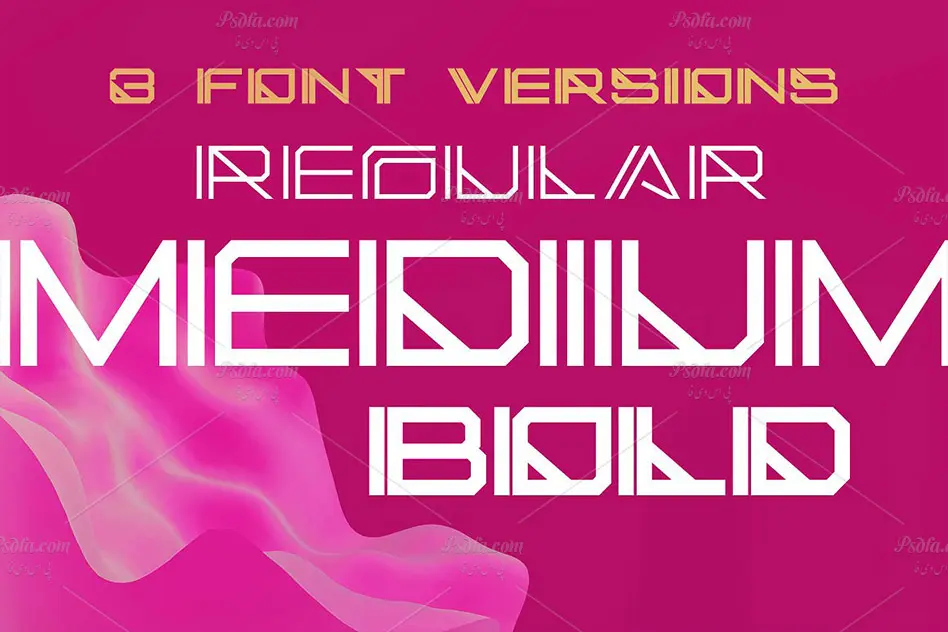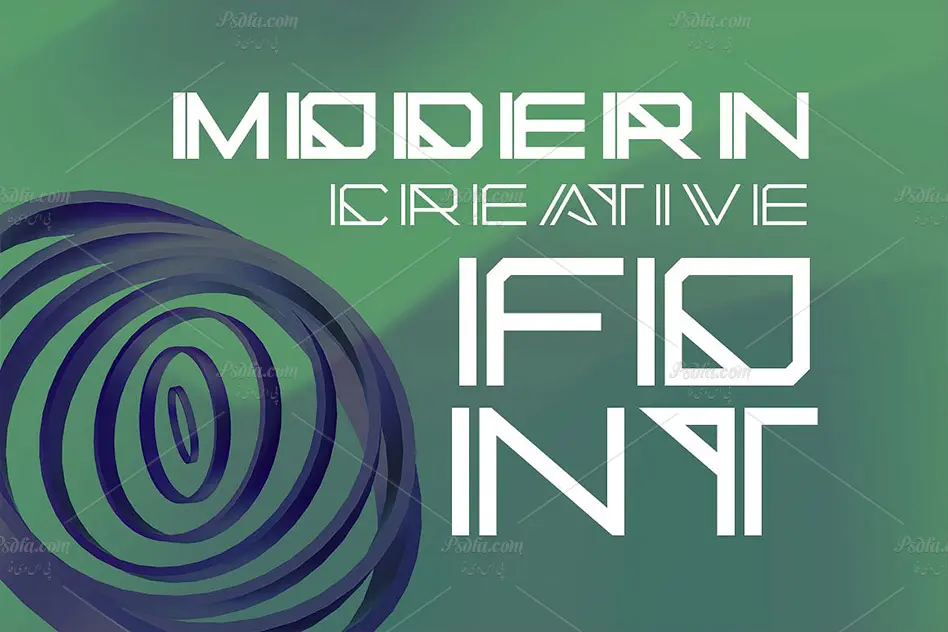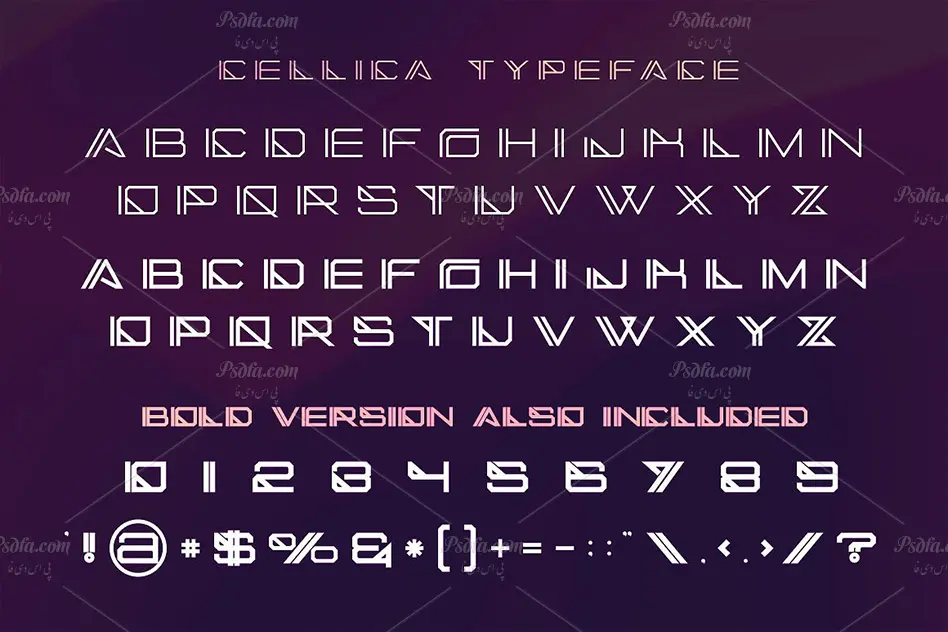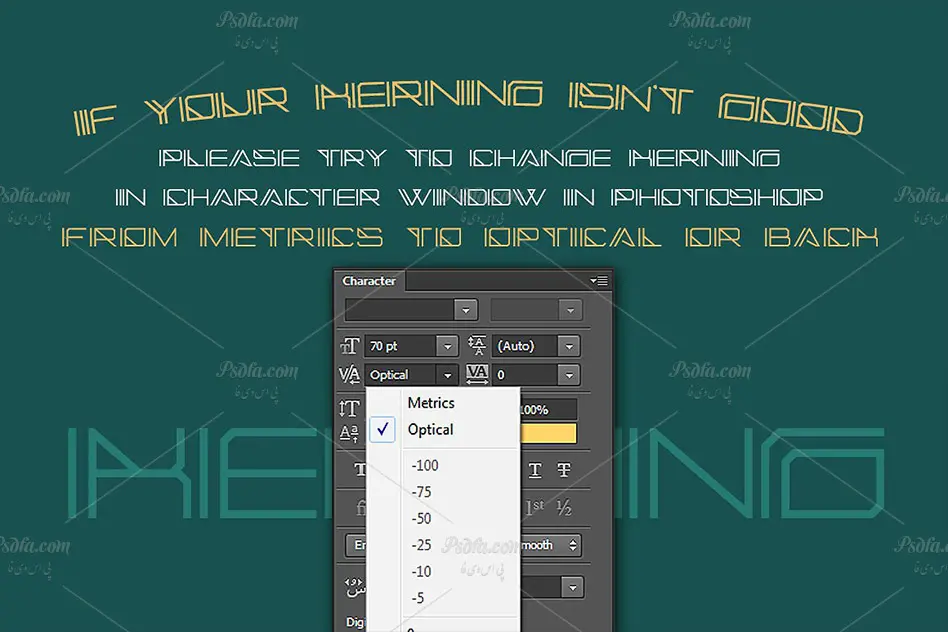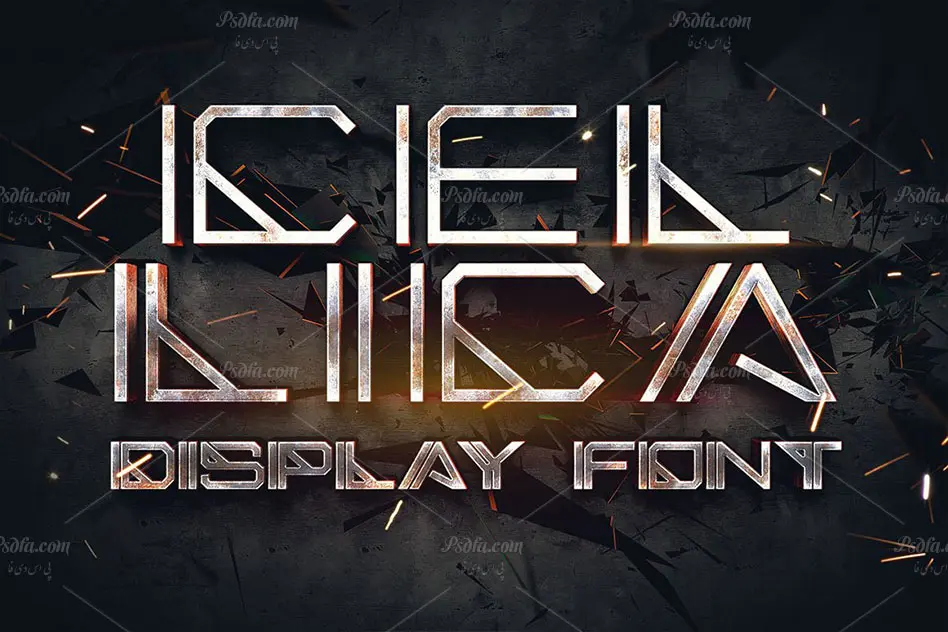
در این قسمت از سایت شاهد فونت نمایشی انگلیسی Cellica Display Font مناسب جهت استفاده در طراحی و گرافیک به خصوص طراحی انواع لوگو و پوستر می باشید. این فونت زیبا در قالب فایل های otf و ttf بر روی سایت بارگذاری شده اند که پس از نصب فایل ها در پوشه فونت های سیستم قادر به استفاده از آن ها در تمام نرم افزارهای گرافیکی و ویرایشگر متن خواهید بود. فونت Cellica در وزن های مختلف معمولی (Regular) ، متوسط (Medium) ، کلفت (Bold) و گرانج (Grunge) طراحی شده است. همچنین نسخه وب این فونت در فایل فشرده موجود است که می توان در طراحی صفحات وب نیز از آن استفاده نمود.
- نام فونت : Cellica
- وزن : Regular , Medium , Bold , Grunge